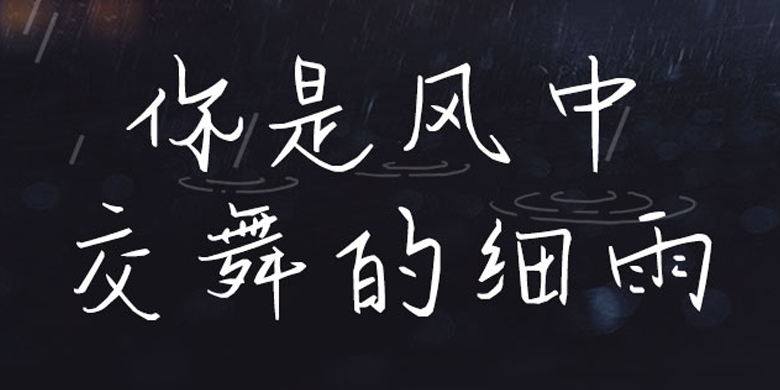
方正手迹-你是风中交舞的细雨
字体品牌: 方正手迹 设计师:余丹 字体分类:常规书写·硬笔 字体属性:精品字 字符集:简繁扩展(GBK) 发布时间: 2020
这款字体风格向党独特,艺术个性鲜明,中宫较大,翘起的撇捺给字体添加了一股俏皮。虽然笔法朴拙,总能给使用者带来一股愉悦的气息。适用于文艺类的书刊、品牌广告和产品包装设计,以及社交网络的个性化用字。